我们倾向于不太考虑字体-我们一直在使用Arial,Verdana,Georgia和Helvetica,并且从不注意它们。这就是为什么大赦国际的新字体如此有趣的原因,他们说新字体会促进有关互联网隐私的对话。会让人说话吗?真的可以使您上网更安全吗?
遇见突变字体
大赦国际的新想法被称为“突变字体"。使用Mutant字体很简单:只需访问网站(www.mutantfont.com/en),然后输入要防止窥视的秘密文本。单击“生成字体",复制代码,并将其粘贴到您的博客中。文本是人类可读的,但给机器带来了困难。
“变体字体"有两种方法使监视和审查机器人变得更加困难:显示在屏幕上的光学部件以及位于代码中的代码在它后面。两者都可以被监视,并且字体具有针对两者的解决方案。首先让我们看一下显示的部分。
字体有七种不同的变体,每种变体都添加了“图形干预"。例如,“突变波浪"显示每个字母后面的波浪线,“快速突变"具有从每个字母左侧伸出的水平线,“突变正方形"在每个字母周围显示许多不同大小的正方形。这些干预措施旨在防止视觉字符识别拾取您发布的字母和单词,而又不会使人们难以阅读。网站上显示的字体每24小时更改一次,因此使机器难以学习阅读所写内容。
表示字体的代码每24小时也更改一次,从而使字体更难使机器可以获取特定网页上正在讨论的内容。大赦国际在上面发布的信息视频说,有成千上万的代码,但是很容易想象这个数字会迅速增长到成千上万,这使得机器很难挑选出图案。
在每24小时更改一次,使用一组特殊的代码以及使用许多图形干预之间,创建Mutant字体时考虑了Internet隐私。想看一下这里的样子吗?这是Mutant字体的一部分文字:
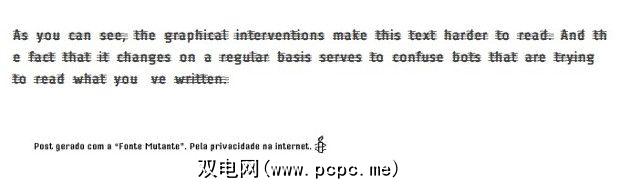
因为Mutant字体仍然是新的,所以我无法找到任何测试来验证它是否可以抵抗任何实际的监视软件。美国国家安全局,GCHQ,中国情报机构和其他类似机构正在使用数据抓取技术是一个很好的选择,但是Mutant Font如何防止这种情况尚待观察。
国际特赦组织还没有对这种字体的实际有效性进行了任何声明,并将其主要描述为启动对话和传播有关Internet隐私问题的意识的一种方式。 。 。
And while the graphical interventions might make it harder for consumer-level optical character recognition to figure out what’s being written, I doubt it would get past government-level software.
仍然,我希望Mutant Font能够引起一些人谈论他们需要做些什么来保持在线安全。关于社交网络上的VPN,Tor和隐私的讨论会更好,但是我们必须从某个地方开始。